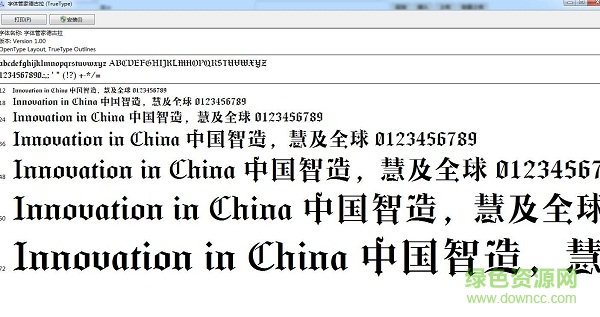
字體管家德古拉
字體管家德古拉是一款裝飾性很強(qiáng)的創(chuàng)意字體,字形非常華麗,個(gè)性鮮明,剛?cè)岵?jì),支持中英文輸入,和哥特式字體非常相似,喜歡的小伙伴快來下載吧!
德古拉字體特色
字型修長,比較重視線條,字體結(jié)尾處的小圓曲線增加了靈動(dòng)性,花紋的變化也采用了植物做裝飾。